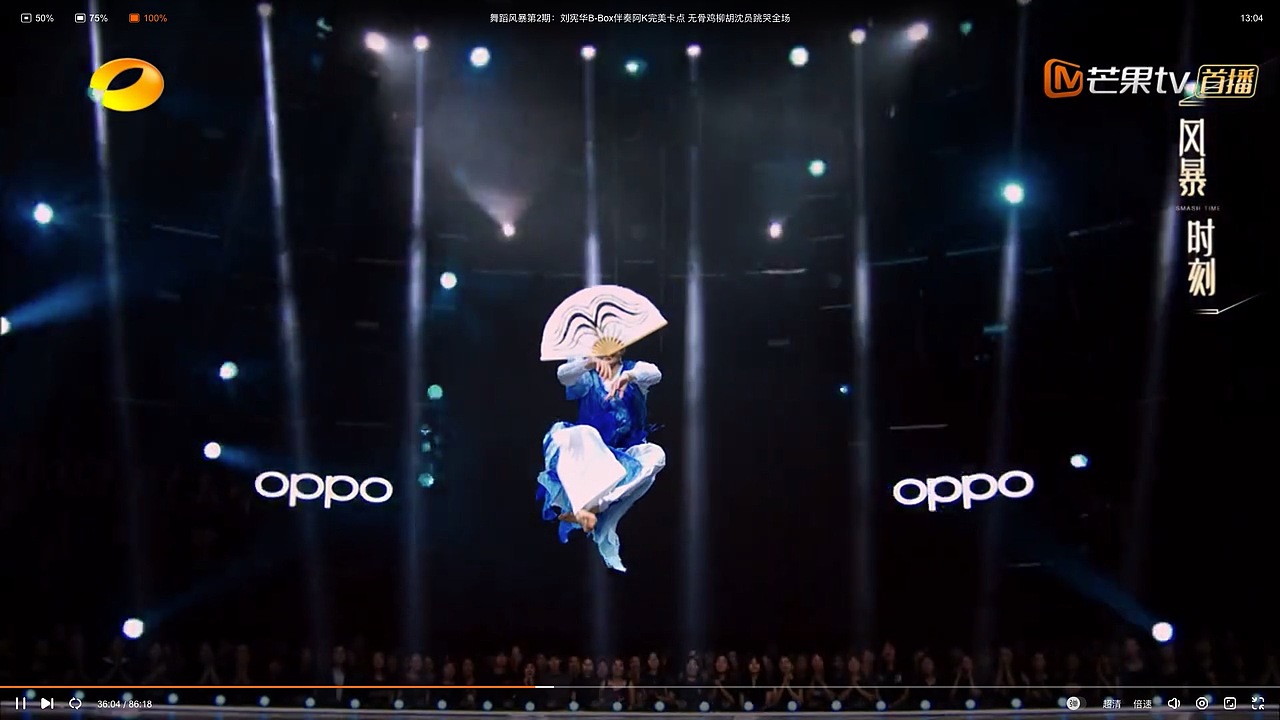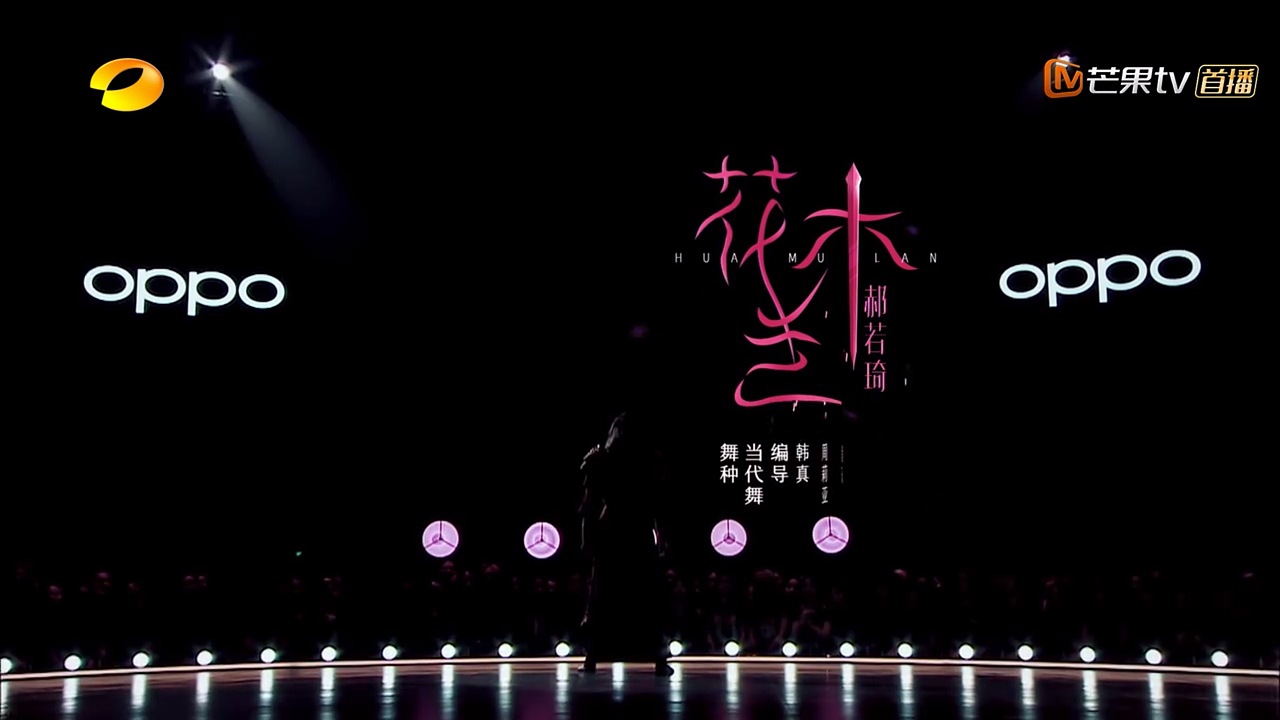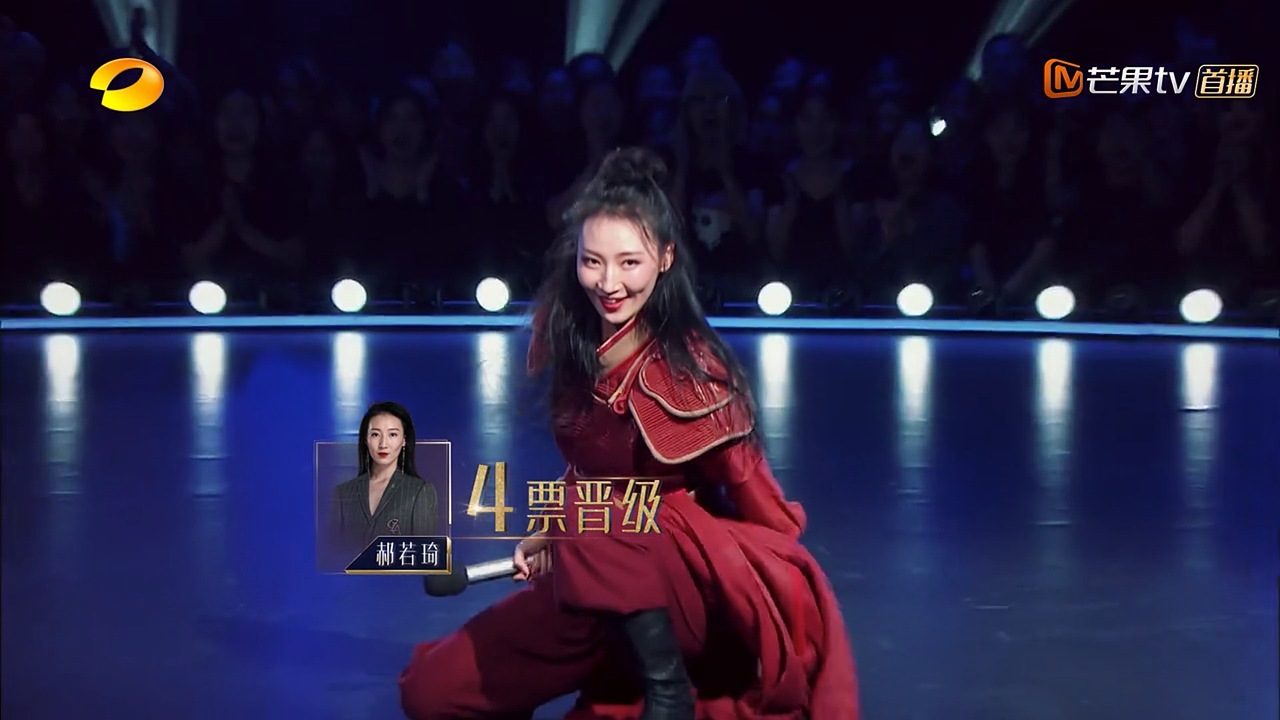
舞蹈风暴的造型和字体欣赏
最近有一批综艺黑马,没有海报,没有宣传,直接播出了,口碑大好,舞蹈动作,造型设计,演员气质都太美了。
看得时候一阵阵的震撼,其中有一条弹幕这样说:看一个哭一个,世界上优秀的人怎么这么多啊~
跟作品气质统一的字体设计,也是一道美丽的风景线。
一大批截图即将来袭(按节目顺序放好,光截图就花了两小时,实在是忍不住又看了一遍,哈哈),如果没有oppo巨大的logo,还一片干净的背景就完美了~
惊艳时刻太多了。